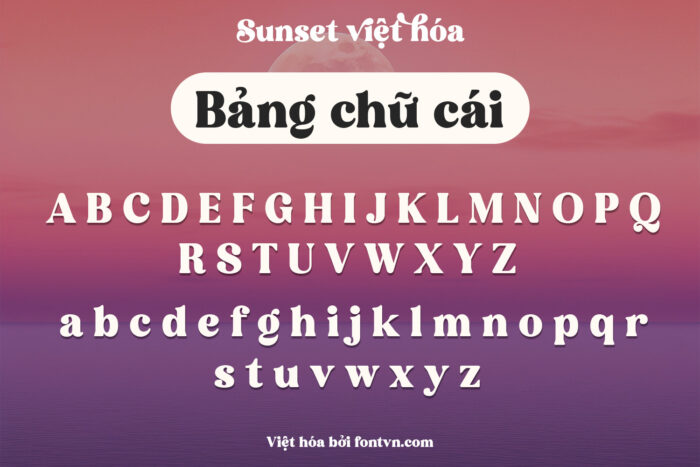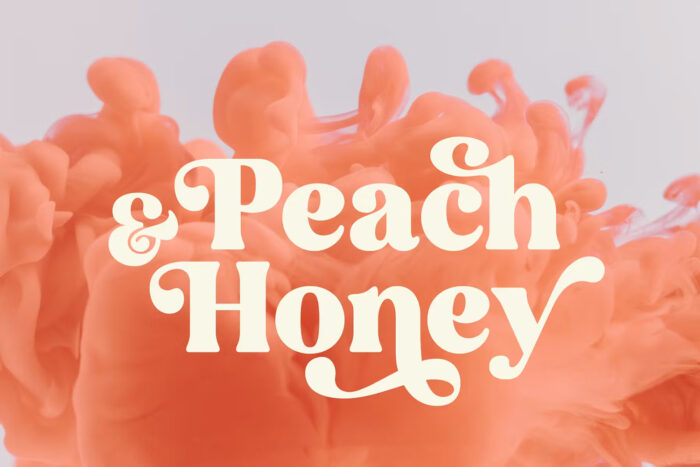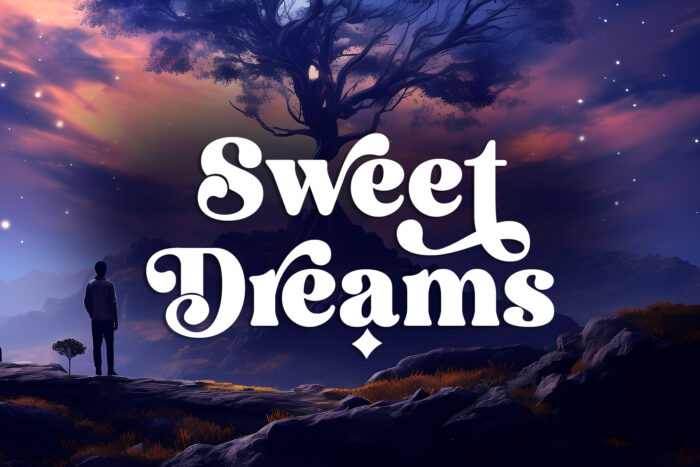
Sunset Việt hóa – Font chữ cổ điển với nhiều biến thể tuyệt đẹp
Sunset là một phông chữ đầy phong cách. Nó có cả vẻ ngoài hiện đại và cổ điển. Tạo các tiêu đề táo bạo, lộng lẫy và thiết kế trang nhã với nét tinh tế cổ điển. Các đường nét tương phản và phần cuối cong của George mang lại vẻ bóng bẩy, trang nhã cho logo, thiệp ngày lễ, thiệp mời đám cưới, câu trích dẫn, quảng cáo, v.v. Phông chữ này có hơn 50 kiểu chữ thay thế và chữ ghép độc đáo giúp mang lại cho logo, danh thiếp và một dự án khác của bạn một diện mạo cổ điển độc đáo. Nó cũng có phiên bản in nghiêng nên thật là một phông chữ cổ điển hoàn hảo!